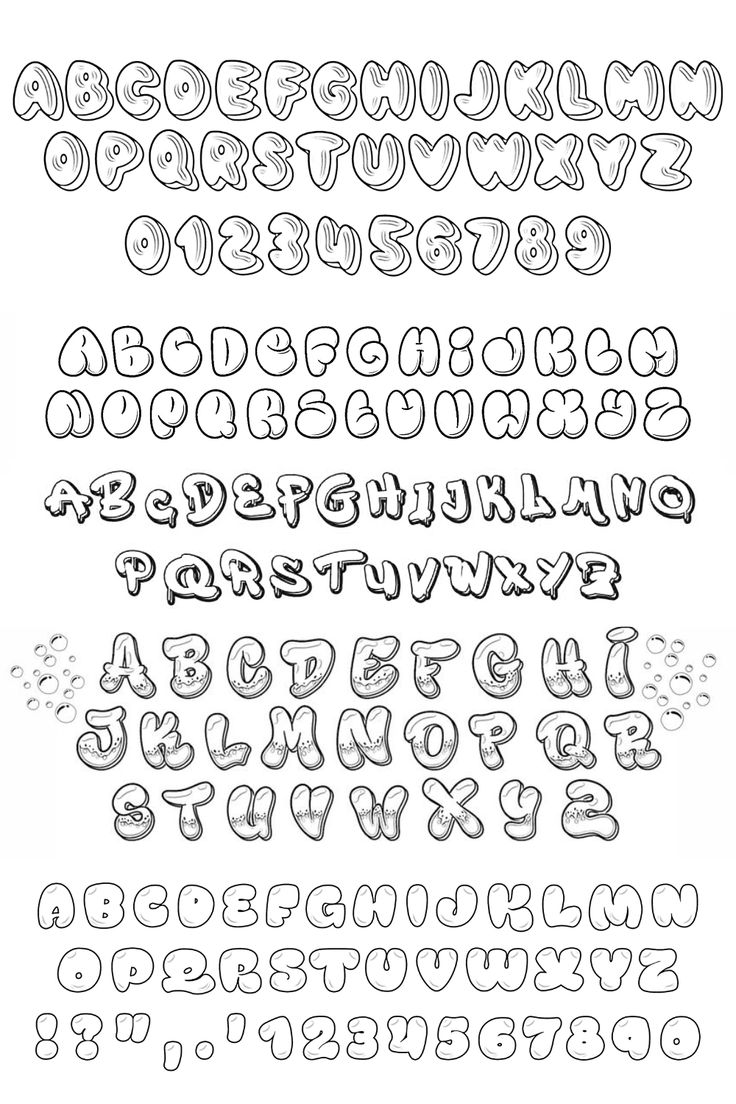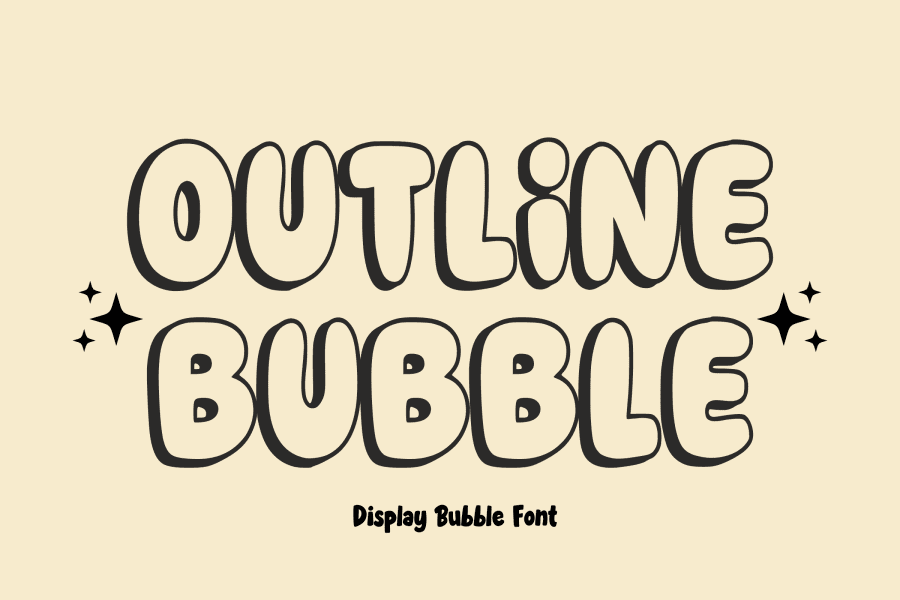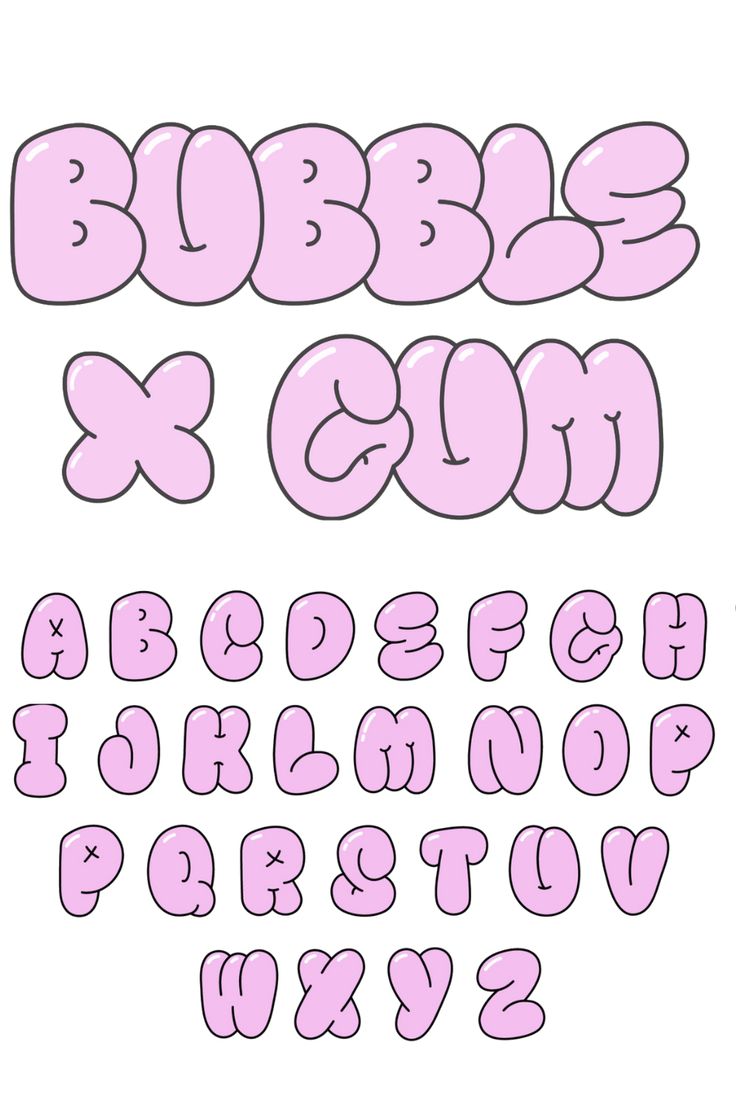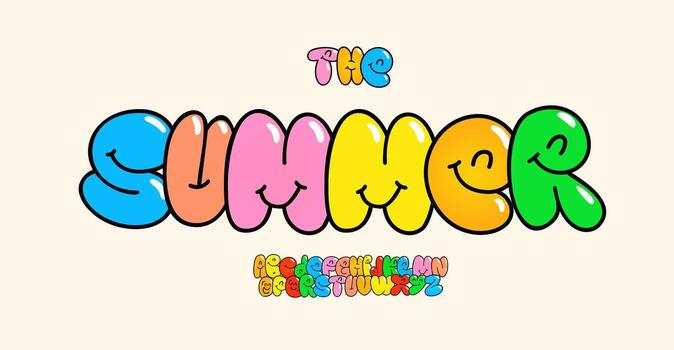
Bubble font là gì?
Bubble font là phong cách phông chữ thuộc dòng Display, mang đặc trưng là các nét chữ tròn trịa, căng mọng như được thổi phồng bởi không khí. Điểm nhấn của Bubble font chính là sự vui tươi, đáng yêu và đầy tính ngẫu hứng, gợi nhắc đến thế giới tuổi thơ và sự sáng tạo không giới hạn.
Vẻ đẹp của Bubble font nằm ở khả năng tạo hiệu ứng 3D mạnh mẽ ngay cả trên mặt phẳng 2D. Tuy nhiên, do nét chữ rất dày, Bubble font thường gặp khó khăn khi xử lý các dấu tiếng Việt sao cho không bị rối mắt. Bản tải font chữ Bubble Việt hóa tại In Viva đã được xử lý kỹ lưỡng từng ký tự đặc thù, đảm bảo các dấu thanh nằm đúng vị trí và không làm hỏng cấu trúc “bong bóng” của bộ chữ, giúp bản thiết kế của bạn luôn rạng rỡ.
Lưu ý: Với Bubble font Việt hóa, bạn nên tận dụng các bảng màu rực rỡ để làm nổi bật nét chữ tinh nghịch, giúp bao bì sản phẩm thu hút các bạn nhỏ từ xa.
Ứng dụng Bubble font Việt hóa trong thiết kế và sản xuất
Vẻ đáng yêu của Bubble font giúp các ấn phẩm trở nên sinh động và gần gũi hơn:
- Thiết kế tem nhãn dán: Bubble font phù hợp để làm các mẫu sticker dán hũ kẹo hoặc nhãn tên cho học sinh mầm non nhờ phong cách vui nhộn, dễ gần.
- Sản xuất hộp: Chữ Bubble in dập nổi trên hộp giấy Ivory tạo cảm giác hào hứng và tò mò cho các bé ngay từ cái nhìn đầu tiên.
- In ấn đồng phục: Slogan dùng font Bubble in chuyển nhiệt trên áo thun tạo vẻ ngoài vô cùng dễ thương cho các bé trong các hoạt động ngoại khóa.
- Trang trí túi giấy: Phông chữ này giúp bộ sản phẩm cho học đường trở nên sinh động và chuyên nghiệp hơn trong mắt phụ huynh.
Khi sử dụng font chữ Bubble, bạn cần lưu ý gì?
Để thiết kế ấn phẩm sử dụng font Bubble đạt độ chính xác cao, designer cần lưu ý:
- Kiểm soát hốc chữ khi in nhỏ: Bubble font có các hốc chữ rất nhỏ (như chữ ‘e’, ‘a’). Khi in tem nhãn siêu nhỏ, bạn nên nới rộng font để tránh tình trạng mực bị lấp đầy khoảng trống.